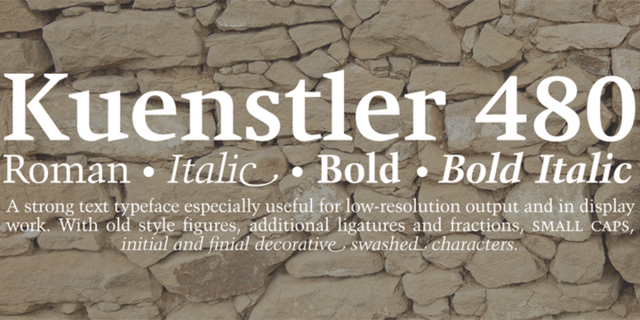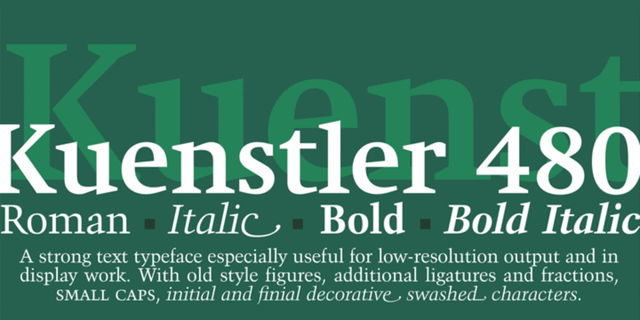
Kuenstler 480 (5 шрифтів)
Опис гарнітури Kuenstler 480Версия фирмы Bitstream шрифта Trump Mediaeval фирмы Linotype, 1954-60. Возможно, это лучший шрифт плодовитого немецкого дизайнера Георга Трумпа, интерпретация антиквы старого стиля. Отличается энергичным рисунком прямого начертания и курсивом, образованным наклоном прямого начертания, за исключением букв a, e, f. Характерный резкий угловатый рисунок строчных и клинообразные засечки Trump Mediaeval напоминают шрифты, высеченные в камне. Это хороший текстовой шрифт с высокой удобочитаемостью, особенно для выводных устройств низкого разрешения, но он может быть полезен и для акцидентного набора. Кириллическая версия разработана для компании ParaType и выпущена в 2010 году (дизайнеры Владимир Ефимов, Изабелла Чаева). В ней сохранены особенности курсивных строчных знаков как наклонных, за исключением г, д, и, й, n, т. В гарнитуре во всех начертаниях разработаны минускульные цифры, дополнительные лигатуры и дроби, а в прямом нормальном начертании – капитель. Сверхжирное начертание добавлено Владимиром Ефимовым в 2011 году.